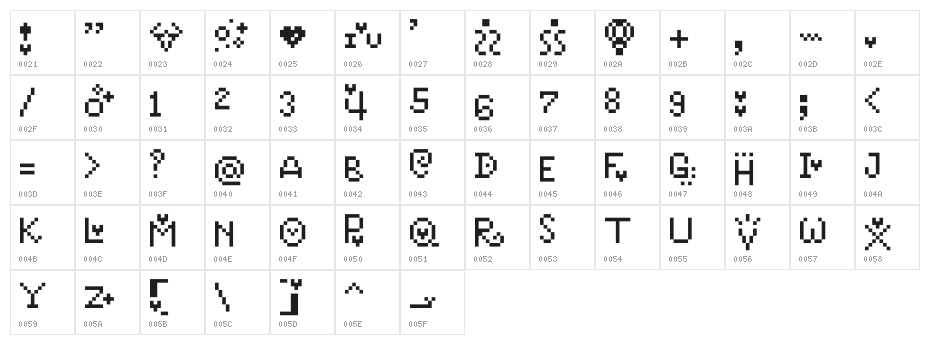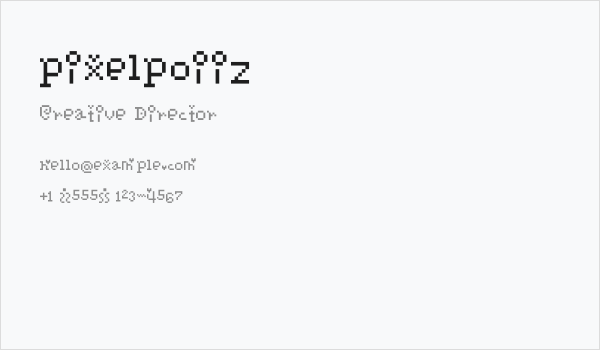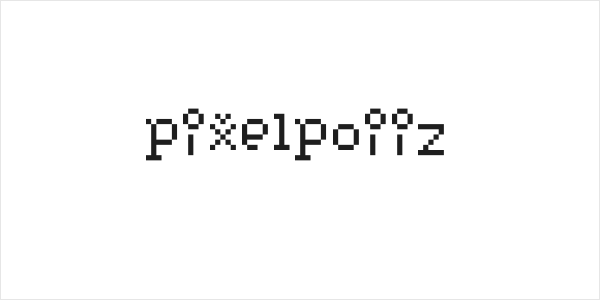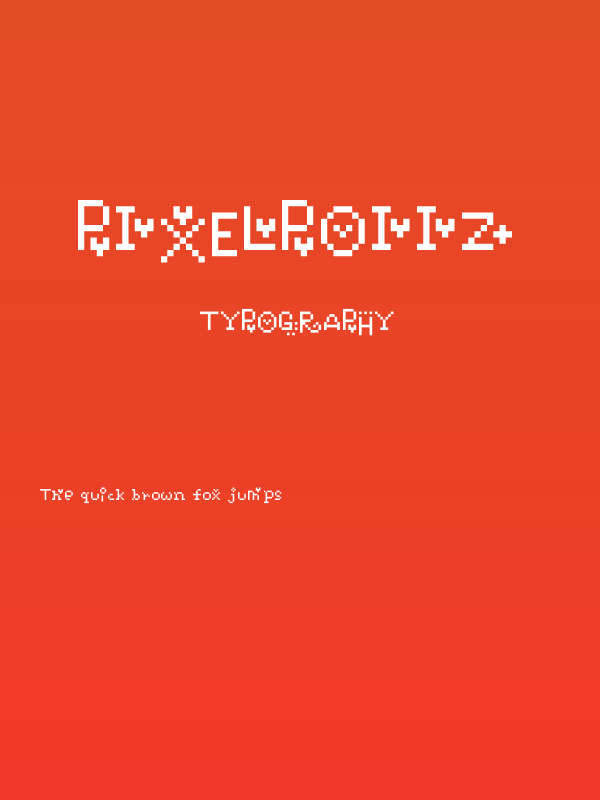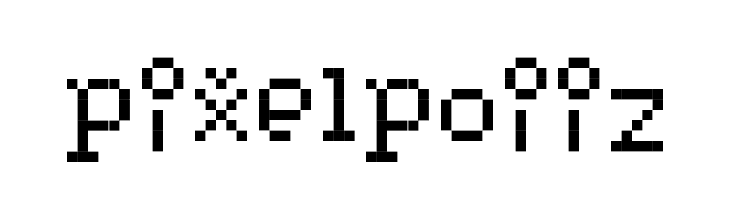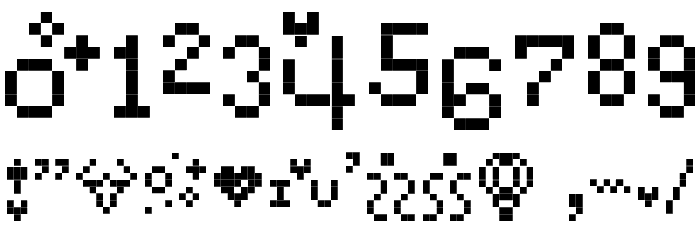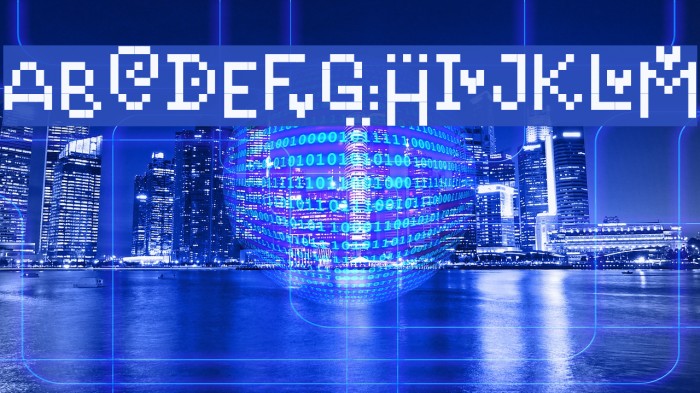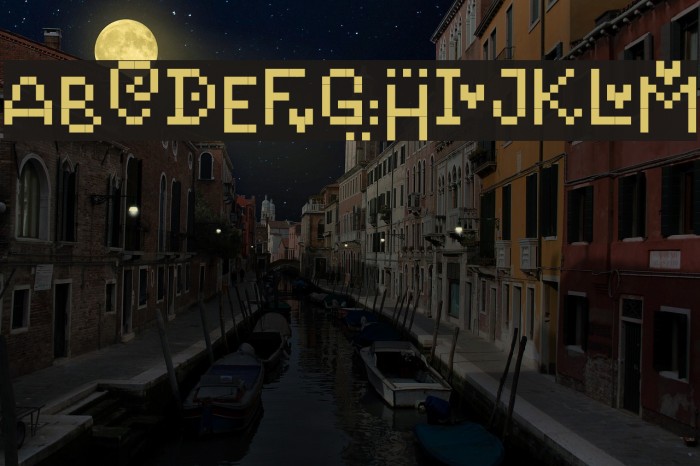
pixelpoiiz Font
| Progetti proposti | Ideal for video game design, retro-themed posters, digital art projects, and any creative work that requires a nostalgic digital touch. |